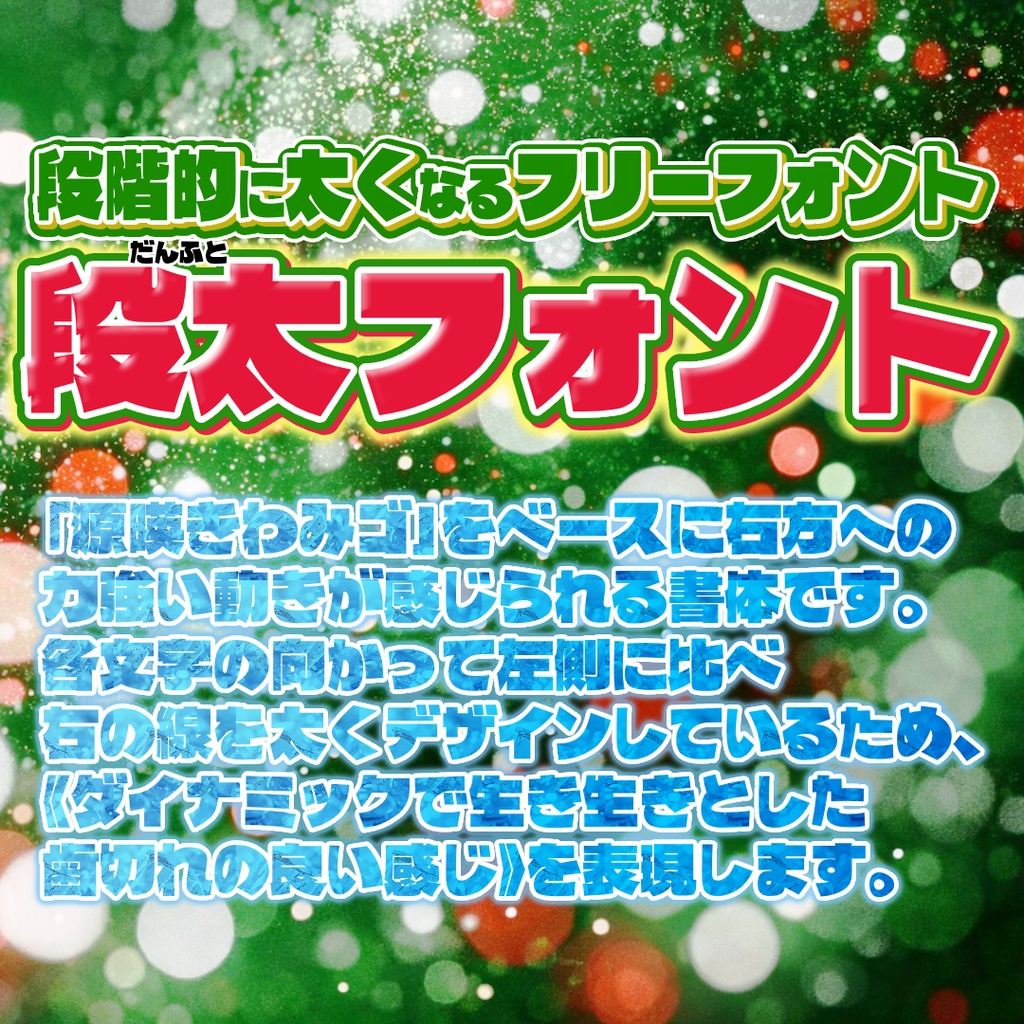
段太フォント【フリーフォント】
段太(だんふと)フォント 概要 「源暎きわみゴ」をベースに右方への力強い動きが感じられるユニークな書体です。 各文字の向かって左側に比べ右の線を太くデザインしているため、 《ダイナミックで生き生きとした歯切れの良い感じ》を表現します。 中身は同じですが、投げ銭版もございます。ご支援いただけましたら幸いです。 ライセンス 当フォントはSIL Open Font License1.1の下で公開いたします。 個人利用・商用利用にかかわらず無償で使用可能です。 SILライセンスにつきましては以下をご確認ください。 ライセンス原文 http://scripts.sil.org/OFL ライセンス原文日本語サイト https://licenses.opensource.jp/OFL-1.1/OFL-1.1.html ライセンスざっくり解説 https://tanukifont.com/sil/ 免責事項 当フォントの使用に関しては全て無保証とさせていただきます。 謝辞 全ての関係者の皆様に深くお礼申し上げます。 源暎きわみゴ https://okoneya.jp/font/genei-kiwamigo.html 詳細 お問い合わせ等ございましたらBOOTHの「ショップへのお問い合わせ」よりお願い致します。 段太フォント 制作:やっちゃん https://yattyann.booth.pm/ フォント公開・利用規約制定 2025年12月24日